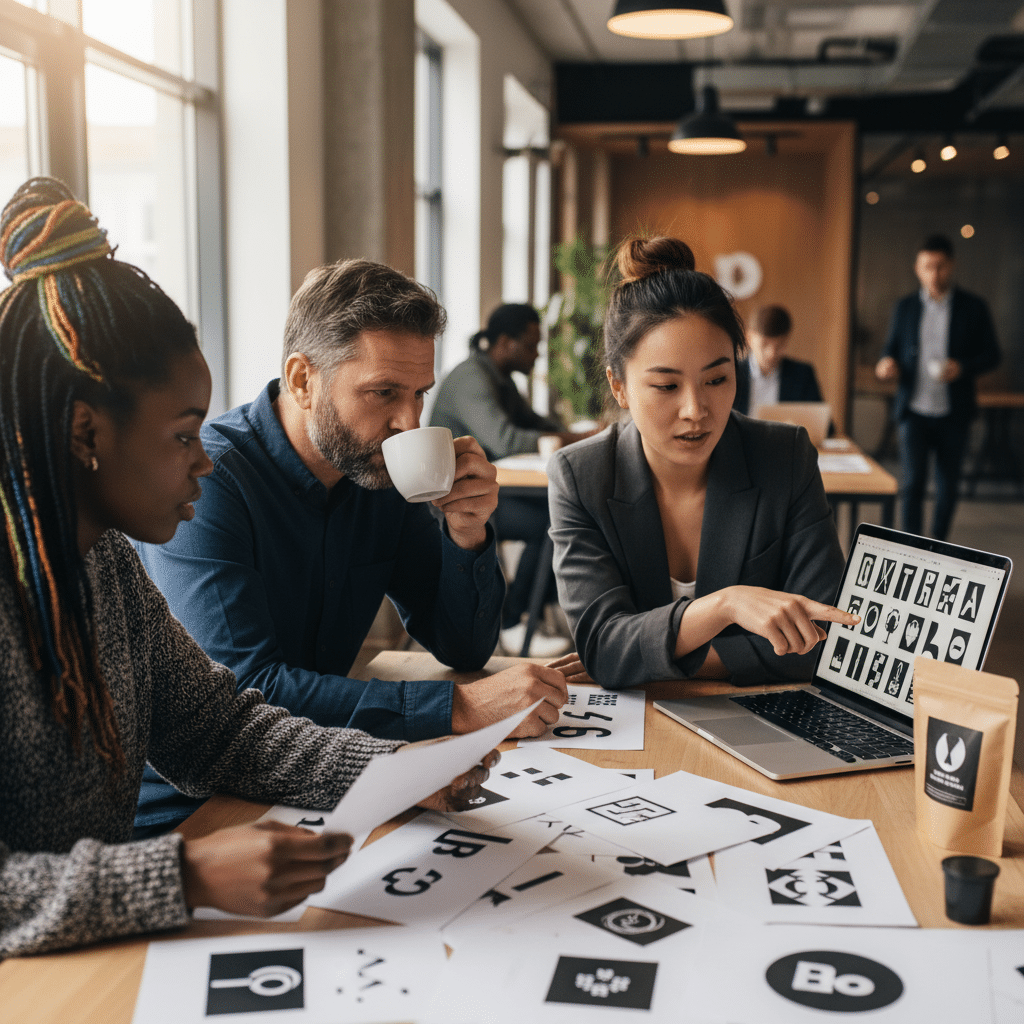
ฟอนต์เปลี่ยนแบรนด์! เลือกฟอนต์อย่างไรให้ลูกค้าจำได้
การเลือกแบบอักษรหรือฟอนต์ (Font) เป็นมากกว่าการตัดสินใจด้านความสวยงาม แต่เป็นองค์ประกอบเชิงกลยุทธ์ที่สำคัญอย่างยิ่งต่อการสร้างอัตลักษณ์ของแบรนด์ (Brand Identity) โดยเฉพาะสำหรับผู้ประกอบการ SME ที่ต้องการสร้างความโดดเด่นในตลาดที่มีการแข่งขันสูง ฟอนต์ทำหน้าที่เป็น “เสียง” ที่มองเห็นได้ของแบรนด์ สามารถสื่อสารบุคลิก ค่านิยม และสร้างการรับรู้ในใจของผู้บริโภคได้อย่างทรงพลัง
สรุปประเด็นสำคัญ
- ฟอนต์คือเสียงและบุคลิกของแบรนด์ ทำหน้าที่สื่อสารอารมณ์ ค่านิยม และสร้างความประทับใจแรกเห็นโดยไม่ต้องใช้คำพูด
- การเลือกประเภทฟอนต์หลัก เช่น Serif หรือ Sans Serif ต้องสอดคล้องกับภาพลักษณ์ของแบรนด์และจิตวิทยาของกลุ่มเป้าหมาย เพื่อสร้างการเชื่อมโยงทางอารมณ์
- ความชัดเจนในการอ่าน (Legibility) เป็นปัจจัยสำคัญที่สุด ฟอนต์ต้องสามารถอ่านได้ง่ายในทุกขนาดและบนทุกสื่อ ตั้งแต่ฉลากสินค้าขนาดเล็กไปจนถึงป้ายโฆษณาขนาดใหญ่
- การใช้ฟอนต์อย่างสม่ำเสมอในทุกช่องทางการสื่อสาร ช่วยสร้างการจดจำแบรนด์ (Brand Recognition) และเสริมสร้างความน่าเชื่อถือในระยะยาว
- การปรับเปลี่ยนฟอนต์เป็นกลยุทธ์สำคัญในการ Rebranding เพื่อปรับภาพลักษณ์ให้ทันสมัยและเข้าถึงกลุ่มเป้าหมายใหม่ๆ แต่ต้องดำเนินการอย่างระมัดระวัง
ความสำคัญของฟอนต์: เสียงที่มองเห็นของแบรนด์
ในโลกธุรกิจปัจจุบัน การสร้างแบรนด์ให้เป็นที่จดจำเป็นสิ่งท้าทาย การใช้ ฟอนต์เปลี่ยนแบรนด์! เลือกฟอนต์อย่างไรให้ลูกค้าจำได้ จึงไม่ใช่คำกล่าวเกินจริง เพราะฟอนต์คือองค์ประกอบแรกๆ ที่ลูกค้าสัมผัสผ่านโลโก้ บรรจุภัณฑ์ เมนูอาหาร หรือเว็บไซต์ มันทำหน้าที่กำหนดโทนและบุคลิกภาพของแบรนด์ก่อนที่ลูกค้าจะได้อ่านข้อความเสียอีก การเลือกฟอนต์ที่เหมาะสมสามารถเปลี่ยนภาพลักษณ์ของแบรนด์ให้ดูน่าเชื่อถือ พรีเมียม หรือเป็นมิตรได้ทันที ในทางกลับกัน การเลือกฟอนต์ที่ไม่สอดคล้องอาจสร้างความสับสนและบั่นทอนความไว้วางใจของลูกค้า
สำหรับธุรกิจ SME การลงทุนเวลาเพื่อเลือกฟอนต์ที่ใช่ถือเป็นการลงทุนที่คุ้มค่า เพราะมันช่วยสร้างรากฐานที่แข็งแกร่งให้กับ Brand Identity ฟอนต์ที่ดีจะช่วยเพิ่มประสิทธิภาพในการสื่อสาร ทำให้ข้อความทางการตลาดโดดเด่นและน่าจดจำ นอกจากนี้ยังช่วยสร้างความแตกต่างจากคู่แข่งในตลาด ลองจินตนาการว่าแบรนด์หรูอย่าง Rolex เปลี่ยนไปใช้ฟอนต์ลายมือแบบเด็กๆ หรือบริษัทเทคโนโลยีล้ำสมัยใช้ฟอนต์แบบพู่กันจีนโบราณ ความรู้สึกที่ลูกค้ามีต่อแบรนด์เหล่านั้นจะเปลี่ยนไปในทันที นี่คือพลังของฟอนต์ในการสร้างหรือทำลายการรับรู้ของแบรนด์
ประเภทฟอนต์และจิตวิทยาที่ซ่อนอยู่
การทำความเข้าใจประเภทของฟอนต์และอารมณ์ที่แต่ละแบบสื่อสารออกมา เป็นกุญแจสำคัญในการเลือกฟอนต์ให้เข้ากับธุรกิจ โดยทั่วไปฟอนต์สามารถแบ่งออกเป็นสองประเภทหลักที่มีผลต่อจิตวิทยาของผู้รับสารอย่างชัดเจน
Serif: ความคลาสสิกและน่าเชื่อถือ
ฟอนต์ประเภท Serif หรือ “ฟอนต์มีเชิง” มีลักษณะเด่นคือมีขีดเล็กๆ ประดับอยู่ที่ปลายของตัวอักษร ซึ่งเป็นรูปแบบที่สืบทอดมาจากการแกะสลักหินในสมัยโรมัน ขีดเล็กๆ เหล่านี้ไม่เพียงแต่ช่วยนำสายตาทำให้อ่านข้อความยาวๆ ได้ง่ายในสื่อสิ่งพิมพ์ แต่ยังแฝงไปด้วยความรู้สึกที่สื่อถึงประวัติศาสตร์ ประเพณี ความสง่างาม และความเป็นทางการ ด้วยเหตุนี้ ฟอนต์ Serif จึงมักถูกเลือกใช้โดยแบรนด์ที่ต้องการสร้างภาพลักษณ์ที่น่าเชื่อถือ มั่นคง และหรูหรา
- บุคลิก: คลาสสิก, เป็นทางการ, หรูหรา, น่าเชื่อถือ, สง่างาม, มีประวัติศาสตร์
- เหมาะสำหรับธุรกิจ: สถาบันการเงิน, ธนาคาร, บริษัทกฎหมาย, มหาวิทยาลัย, แบรนด์แฟชั่นชั้นสูง, โรงแรมหรู, สำนักพิมพ์, สินค้าที่เน้นคุณภาพและประเพณี
- ตัวอย่างฟอนต์: Times New Roman, Garamond, Didot, Bodoni
Sans Serif: ความทันสมัยและเรียบง่าย
คำว่า “Sans” ในภาษาฝรั่งเศสแปลว่า “ไม่มี” ดังนั้นฟอนต์ Sans Serif หรือ “ฟอนต์ไม่มีเชิง” จึงหมายถึงฟอนต์ที่ไม่มีขีดเล็กๆ ที่ปลายตัวอักษร ทำให้มีรูปลักษณ์ที่ดูสะอาดตา เรียบง่าย และทันสมัย ฟอนต์ประเภทนี้ได้รับความนิยมอย่างสูงในยุคดิจิทัล เนื่องจากความคมชัดและความสามารถในการอ่านได้ง่ายบนหน้าจอคอมพิวเตอร์และโทรศัพท์มือถือที่มีความละเอียดแตกต่างกันไป
ฟอนต์ Sans Serif สื่อถึงความตรงไปตรงมา ความสดใหม่ ความเป็นมิตร และนวัตกรรม จึงเป็นตัวเลือกยอดนิยมสำหรับแบรนด์ที่ต้องการสื่อสารภาพลักษณ์ที่เข้าถึงง่ายและก้าวทันโลก
- บุคลิก: ทันสมัย, เรียบง่าย (มินิมอล), สะอาด, เป็นมิตร, ตรงไปตรงมา, ก้าวหน้า
- เหมาะสำหรับธุรกิจ: บริษัทเทคโนโลยี, สตาร์ทอัพ, แบรนด์สินค้าไลฟ์สไตล์, สินค้าสำหรับคนรุ่นใหม่, ธุรกิจที่เน้นนวัตกรรม, แบรนด์ที่ต้องการภาพลักษณ์ที่สดใสและเข้าถึงง่าย
- ตัวอย่างฟอนต์: Helvetica, Arial, Futura, Open Sans
| คุณลักษณะ | Serif (ฟอนต์มีเชิง) | Sans Serif (ฟอนต์ไม่มีเชิง) |
| บุคลิกและอารมณ์ | คลาสสิก, เป็นทางการ, หรูหรา, น่าเชื่อถือ, สง่างาม | ทันสมัย, เรียบง่าย, สะอาด, เป็นมิตร, เข้าถึงง่าย |
| อุตสาหกรรมที่เหมาะสม | การเงิน, กฎหมาย, แฟชั่นชั้นสูง, การศึกษา, สิ่งพิมพ์ | เทคโนโลยี, สตาร์ทอัพ, สินค้าอุปโภคบริโภค, สื่อดิจิทัล |
| การใช้งานหลัก | เหมาะกับข้อความยาวๆ ในสื่อสิ่งพิมพ์, สร้างความน่าเชื่อถือ | เหมาะกับหน้าจอดิจิทัล, โลโก้, หัวข้อที่ต้องการความชัดเจน |
| ตัวอย่างแบรนด์ | Vogue, Tiffany & Co., Rolex | Google, Netflix, Spotify |
5 หลักการเลือกฟอนต์ให้แบรนด์เป็นที่จดจำ
การเลือกฟอนต์ไม่ใช่เรื่องของความชอบส่วนตัว แต่เป็นกระบวนการที่ต้องอาศัยการวิเคราะห์และวางแผนอย่างเป็นระบบ เพื่อให้ได้ผลลัพธ์ที่สอดคล้องกับเป้าหมายทางธุรกิจ หลักการทั้ง 5 ข้อต่อไปนี้จะช่วยเป็นแนวทางสำหรับผู้ประกอบการ SME ในการเลือกฟอนต์ที่ใช่สำหรับแบรนด์
1. สะท้อนบุคลิกและตัวตนของแบรนด์
ก่อนจะเริ่มมองหาฟอนต์ ควรกำหนดบุคลิกของแบรนด์ (Brand Personality) ให้ชัดเจนเสียก่อน แบรนด์ของคุณเป็นแบบไหน? สนุกสนานและเป็นกันเอง? หรือจริงจังและเชี่ยวชาญ? หรูหราและพิเศษ? หรือเรียบง่ายและเข้าถึงได้? คำตอบเหล่านี้จะเป็นเข็มทิศในการเลือกฟอนต์ ฟอนต์ที่เลือกต้องสามารถสะท้อนค่านิยมหลักและตัวตนของแบรนด์ออกมาได้ เช่น หากเป็นแบรนด์สกินแคร์ออร์แกนิกที่เน้นความเป็นธรรมชาติ อาจเลือกใช้ฟอนต์ Sans Serif ที่ดูสะอาดตาและโปร่งสบาย เพื่อสื่อถึงความบริสุทธิ์และเรียบง่าย
2. อ่านง่ายและชัดเจนในทุกขนาด
ความสวยงามของฟอนต์จะไร้ความหมายหากลูกค้าไม่สามารถอ่านข้อความออก นี่คือหลักการที่สำคัญที่สุด ฟอนต์ที่เลือกจะต้องมีความชัดเจนในการอ่าน (Legibility) สูง ต้องทดสอบการแสดงผลของฟอนต์ในหลายๆ ขนาด ตั้งแต่ขนาดเล็กจิ๋วบนฉลากสินค้าหรือนามบัตร ไปจนถึงขนาดใหญ่บนป้ายโฆษณาหรือหน้าเว็บไซต์ และต้องทดสอบบนสื่อที่แตกต่างกัน ทั้งสื่อสิ่งพิมพ์และสื่อดิจิทัล ฟอนต์บางตัวอาจดูสวยงามเมื่อมีขนาดใหญ่ แต่เมื่อย่อเล็กลง รายละเอียดอาจติดกันจนอ่านไม่ออก ดังนั้น ควรเลือกฟอนต์ที่ออกแบบมาอย่างดีและคงความชัดเจนไว้ได้ในทุกสถานการณ์
3. สอดคล้องกับกลุ่มเป้าหมาย
การทำความเข้าใจกลุ่มเป้าหมายเป็นสิ่งสำคัญในการออกแบบทุกองค์ประกอบของแบรนด์ รวมถึงการเลือกฟอนต์ด้วยเช่นกัน จิตวิทยาฟอนต์มีผลต่อการรับรู้และความรู้สึกของคนในแต่ละกลุ่มอายุและวัฒนธรรมที่แตกต่างกัน กลุ่มเป้าหมายที่เป็นคนรุ่นใหม่อาจตอบสนองต่อฟอนต์ Sans Serif ที่ดูทันสมัยได้ดีกว่า ในขณะที่กลุ่มลูกค้าผู้ใหญ่หรือกลุ่มตลาดบนอาจรู้สึกเชื่อมโยงกับความสง่างามและความน่าเชื่อถือของฟอนต์ Serif มากกว่า การเลือกฟอนต์ที่โดนใจกลุ่มเป้าหมายจะช่วยสร้างความสัมพันธ์และทำให้แบรนด์รู้สึก “ใช่” สำหรับพวกเขา
4. รักษาความสม่ำเสมอ หลีกเลี่ยงความซับซ้อน
แบรนด์ที่แข็งแกร่งคือแบรนด์ที่มีความสม่ำเสมอ การใช้ฟอนต์หลายแบบมากเกินไปในงานออกแบบชิ้นเดียวหรือในสื่อต่างๆ ของแบรนด์ จะสร้างความสับสนและทำให้ภาพลักษณ์ดูไม่เป็นมืออาชีพ หลักการที่ดีคือการจำกัดการใช้ฟอนต์ไว้ที่ไม่เกิน 2-3 แบบในระบบการออกแบบทั้งหมด โดยอาจเลือกใช้ฟอนต์เดียวแต่มีหลายน้ำหนัก (เช่น Light, Regular, Bold) เพื่อสร้างลำดับชั้นของข้อมูล หรือเลือกใช้ฟอนต์ 2 แบบที่เข้ากันได้ดี (เช่น Serif สำหรับหัวข้อ และ Sans Serif สำหรับเนื้อหา) เพื่อสร้างคอนทราสต์ที่น่าสนใจ การรักษาความสม่ำเสมอนี้จะช่วยตอกย้ำภาพจำของแบรนด์ให้ชัดเจนยิ่งขึ้น
5. พิจารณาฟอนต์สั่งทำพิเศษเพื่อเอกลักษณ์สูงสุด
สำหรับแบรนด์ที่ต้องการสร้างเอกลักษณ์ที่โดดเด่นและไม่ซ้ำใครอย่างแท้จริง การลงทุนในฟอนต์สั่งทำพิเศษ (Custom Font) ถือเป็นกลยุทธ์ขั้นสูงที่น่าสนใจ แบรนด์ระดับโลกหลายแห่ง เช่น Netflix (Netflix Sans) หรือ Google (Product Sans) ได้สร้างฟอนต์ของตัวเองขึ้นมาเพื่อใช้ในทุกผลิตภัณฑ์และสื่อการตลาด ข้อดีของการมีฟอนต์เฉพาะคือการสร้างความแตกต่างจากคู่แข่งได้อย่างสิ้นเชิง ป้องกันการลอกเลียนแบบ และสามารถออกแบบฟอนต์ให้สะท้อนบุคลิกของแบรนด์ได้อย่างสมบูรณ์แบบ แม้ว่าจะมีค่าใช้จ่ายสูง แต่ผลลัพธ์ที่ได้คือสินทรัพย์ถาวรที่ทรงคุณค่าของแบรนด์
ฟอนต์กับการ Rebranding: โอกาสและความท้าทาย
เมื่อเวลาผ่านไป แบรนด์อาจจำเป็นต้องปรับเปลี่ยนภาพลักษณ์เพื่อให้ทันสมัยหรือเข้าถึงกลุ่มเป้าหมายใหม่ๆ ซึ่งกระบวนการนี้เรียกว่า การ Rebranding และการเปลี่ยนแปลงฟอนต์ก็เป็นส่วนสำคัญอย่างยิ่งในกระบวนการนี้ การปรับฟอนต์สามารถส่งสัญญาณการเปลี่ยนแปลงได้อย่างชัดเจนและรวดเร็ว โดยอาจเป็นการปรับโฉมเพียงบางส่วน (Partial Rebranding) เช่น การเปลี่ยนจากฟอนต์ Serif ที่ดูเก่าแก่เป็นฟอนต์ Sans Serif ที่ดูเด็กลง เพื่อปรับภาพลักษณ์ให้สดใหม่ขึ้น โดยยังคงรักษาแก่นหลักของแบรนด์ไว้ หรืออาจเป็นการปรับโฉมทั้งหมด (Total Rebranding) ซึ่งหมายถึงการยกเครื่องอัตลักษณ์ทางภาพ (Visual Identity) ทั้งหมด รวมถึงการสร้างระบบไทโปกราฟี (Typography) ขึ้นมาใหม่ทั้งหมด
กรณีศึกษา: บทเรียนราคาแพงของ Gap
อย่างไรก็ตาม การเปลี่ยนแปลงฟอนต์ในการ Rebranding ต้องทำอย่างมีกลยุทธ์และสื่อสารให้ดี มิฉะนั้นอาจส่งผลเสียมากกว่าผลดี ตัวอย่างที่มักถูกหยิบยกมาเป็นบทเรียนคือกรณีของแบรนด์เสื้อผ้า Gap ในปี 2010 ที่ตัดสินใจเปลี่ยนโลโก้เดิมซึ่งใช้ฟอนต์ Serif ที่เป็นเอกลักษณ์มานานหลายสิบปี ไปเป็นโลโก้ใหม่ที่ใช้ฟอนต์ Sans Serif อย่าง Helvetica ซึ่งดูธรรมดาและขาดเอกลักษณ์ การเปลี่ยนแปลงนี้เกิดขึ้นอย่างกะทันหันโดยไม่มีการสื่อสารที่เพียงพอ ทำให้เกิดกระแสต่อต้านอย่างรุนแรงจากลูกค้าประจำที่รู้สึกผูกพันกับโลโก้เก่า
ความล้มเหลวของ Gap แสดงให้เห็นว่าฟอนต์และโลโก้ไม่ใช่แค่สัญลักษณ์ทางการค้า แต่เป็นส่วนหนึ่งของความทรงจำและความผูกพันที่ลูกค้ามีต่อแบรนด์ การเปลี่ยนแปลงใดๆ ที่กระทบต่อองค์ประกอบหลักเหล่านี้จึงต้องผ่านการคิดวิเคราะห์อย่างรอบคอบ
ท้ายที่สุด Gap ต้องยอมถอยและกลับไปใช้โลโก้เดิมในเวลาเพียงไม่ถึงหนึ่งสัปดาห์ บทเรียนจากกรณีนี้คือ ฟอนต์มีความสำคัญต่อความรู้สึกของลูกค้ามากกว่าที่หลายคนคิด การเปลี่ยนแปลงต้องมีเหตุผลรองรับและต้องสื่อสารให้ลูกค้าเข้าใจถึงวิสัยทัศน์ใหม่ของแบรนด์
สรุป: สร้างแบรนด์ให้แข็งแกร่งด้วยการเลือกฟอนต์ที่ใช่
การเลือกฟอนต์เป็นหนึ่งในการตัดสินใจเชิงกลยุทธ์ที่สำคัญที่สุดในการสร้างแบรนด์ มันไม่ใช่แค่เรื่องของความสวยงาม แต่เป็นเครื่องมือสื่อสารอันทรงพลังที่สามารถกำหนดการรับรู้ สร้างความน่าเชื่อถือ และทำให้แบรนด์เป็นที่จดจำในใจของลูกค้า สำหรับผู้ประกอบการ SME การใส่ใจในรายละเอียดเล็กๆ น้อยๆ เช่นการเลือกฟอนต์สำหรับโลโก้ เมนูอาหาร หรือการพิมพ์ฉลากสินค้า สามารถสร้างความแตกต่างที่ยิ่งใหญ่และนำไปสู่ความสำเร็จในระยะยาวได้